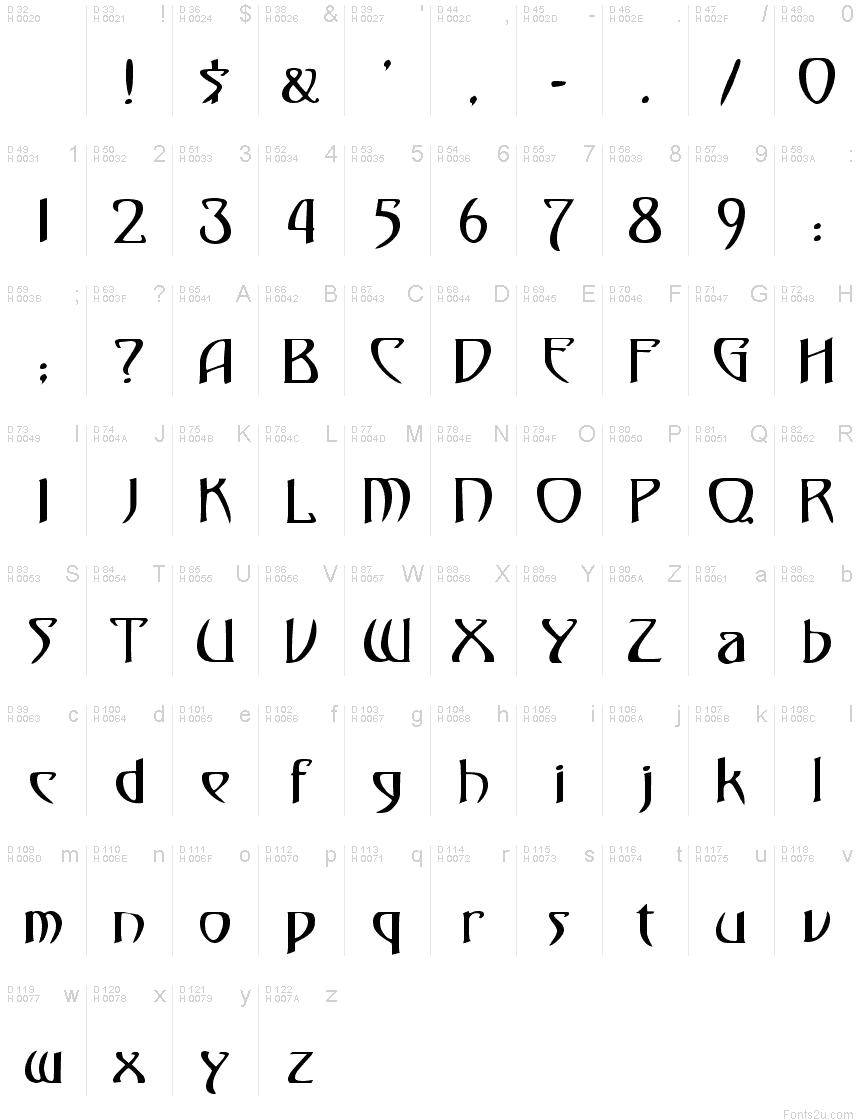
Gismonda to darmowy, utrzymany w stylu retro font typu display o dramatycznym, nasyconym tuszem charakterze. Szerokie krzywizny, żłobione wnętrza liter i zwężające się pociągnięcia przypominają skrzyżowanie dawnego liternictwa plakatowego z gotycką kaligrafią, nadając słowom teatralny, niemal mistyczny wyraz. Litery zazębiają się, tworząc gęsty, rytmiczny układ, który płynnie prowadzi wzrok przez cały napis.
Dzięki Gismonda nadasz wyrazisty, pełen historii głos okładkom książek fantasy, logotypom zespołów gothic, okultystycznym zinom, plakatom w stylu vintage, tytułom gier i grafikom tematycznym. Ten darmowy krój najlepiej sprawdza się w dużych rozmiarach, gdzie jego rzeźbione kształty i ostre akcenty mogą w pełni wybrzmieć; do tekstu głównego dobierz czystą, geometryczną czcionkę bezszeryfową, aby zachować czytelność, podczas gdy Gismonda zadba o dramaturgię.